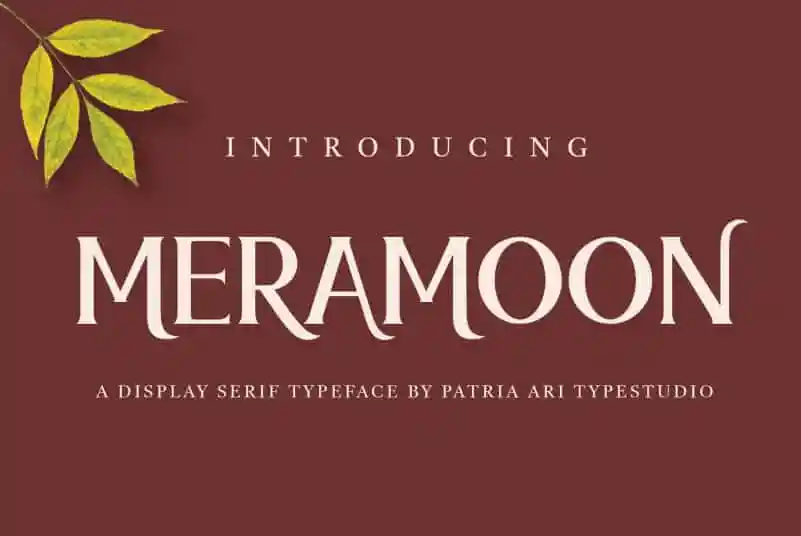
Meramoon Serif Font – Download Grátis
Meramoon Serif Font é uma tipografia sans serif vintage com gílias estéticas alternativas. Esta elegante opção para design gráfico combina um charme clássico moderno que faz dela uma escolha perfeita tanto para projetos de marca quanto para logotipos, posts nas redes sociais, anúncios, embalagens de produtos, designs de produtos, etiquetas e até mesmo para água-marinhas ou desenhos. Suas formas limpas e sutis certamente se encaixam em qualquer projeto que você está lidando – seja ele uma apresentação elegante, um convite ou até mesmo o design de papelarias. Seu estilo único é ideal para complementar seu trabalho de forma a destacar sua personalidade no mundo do design visual.